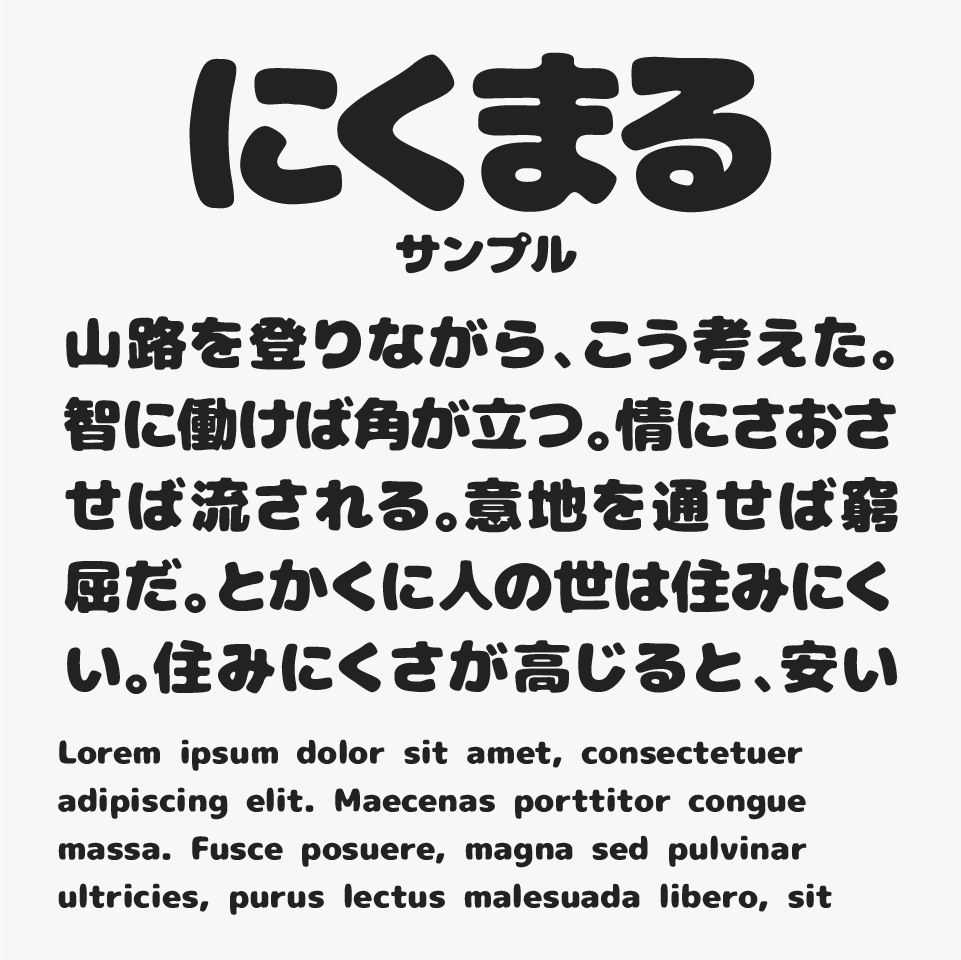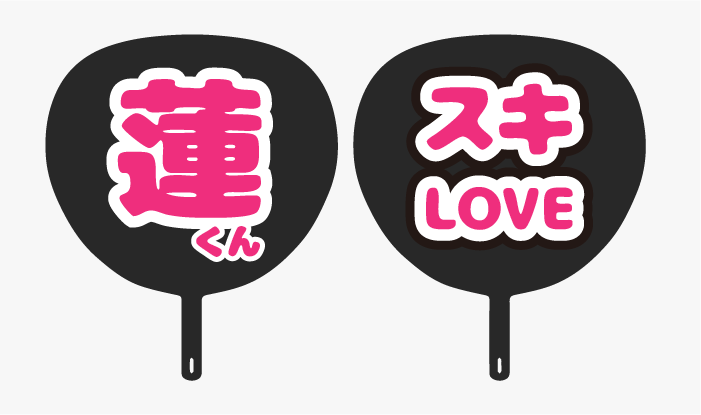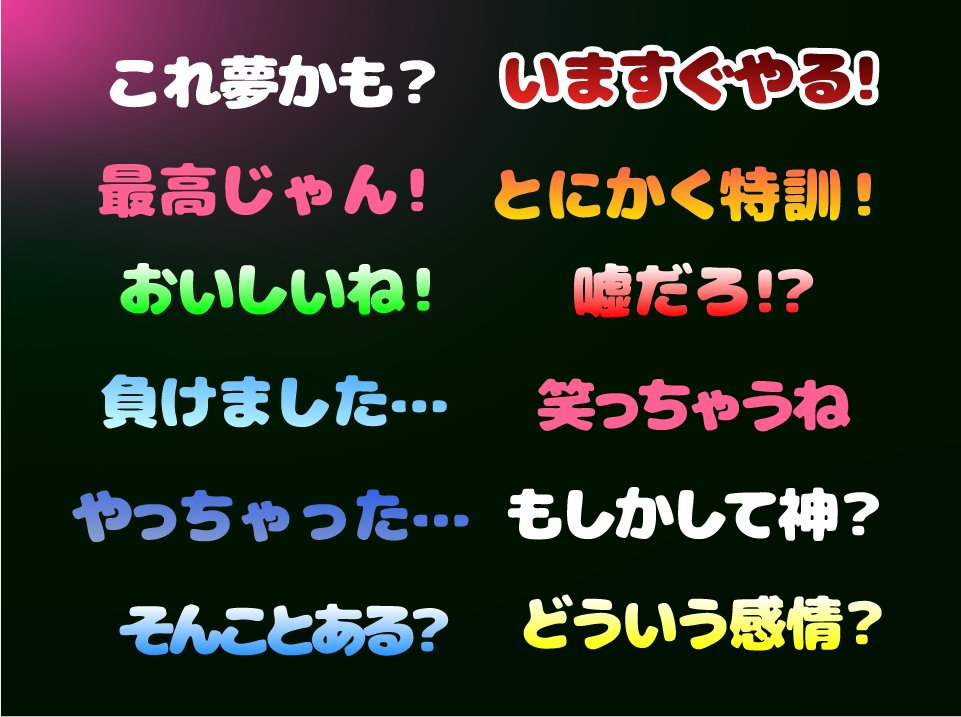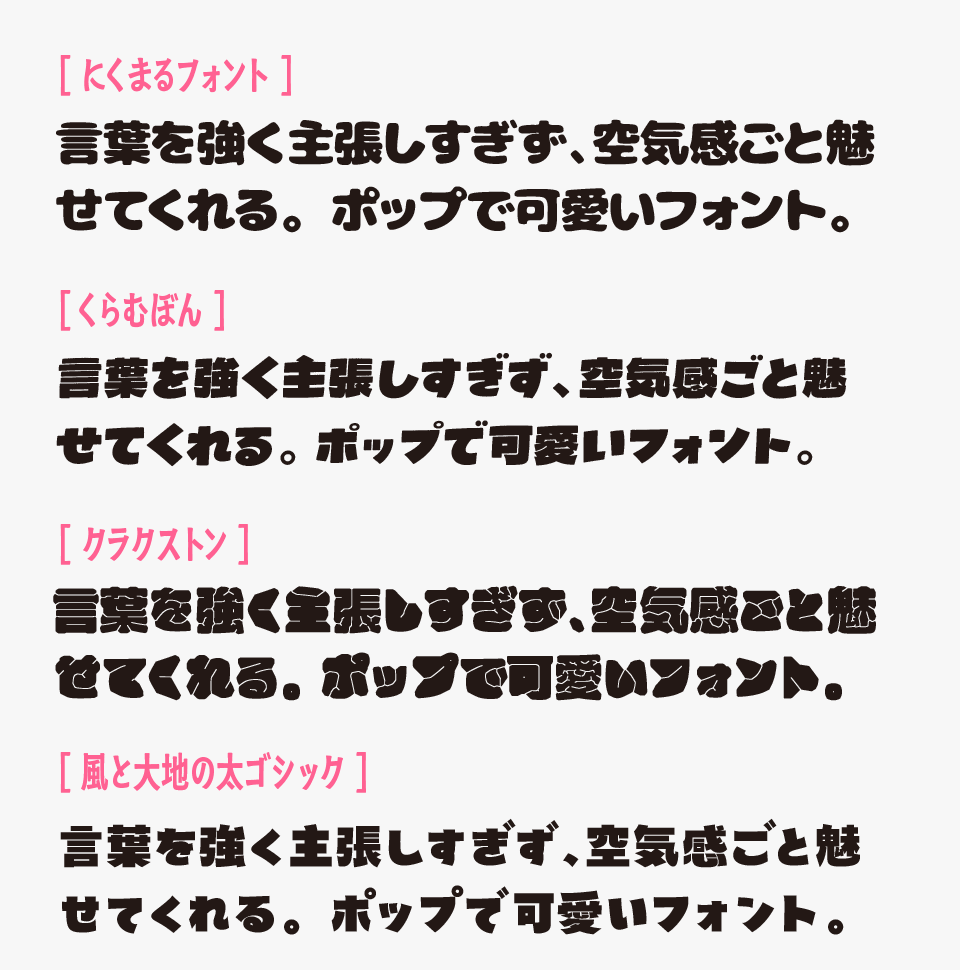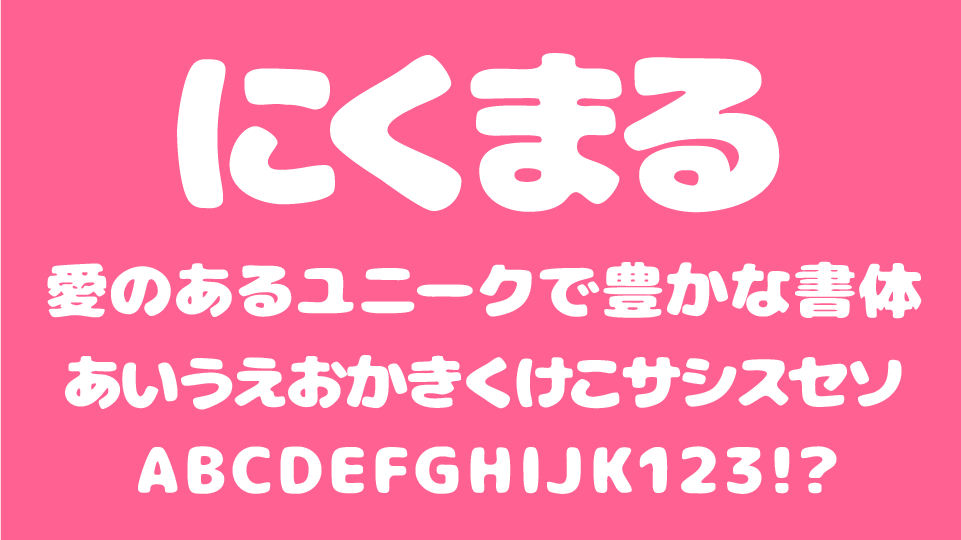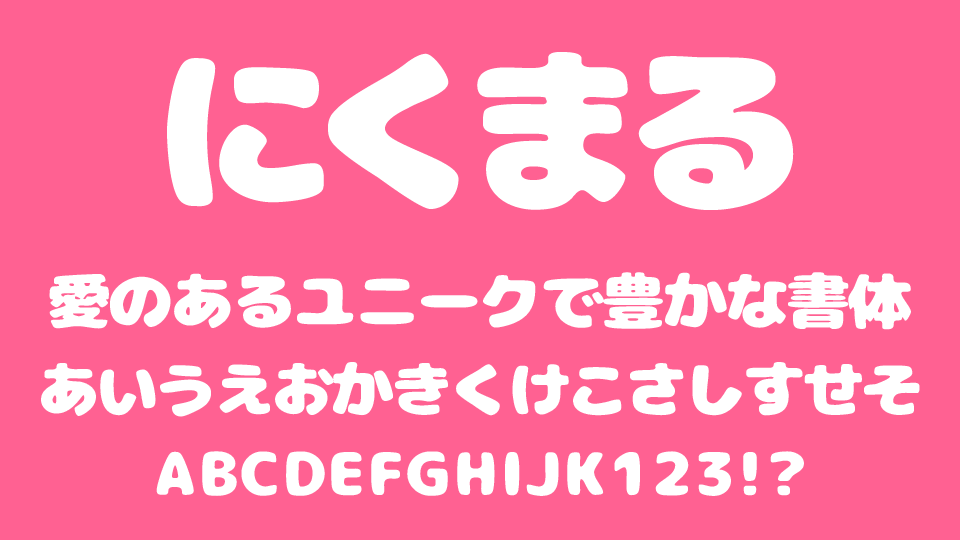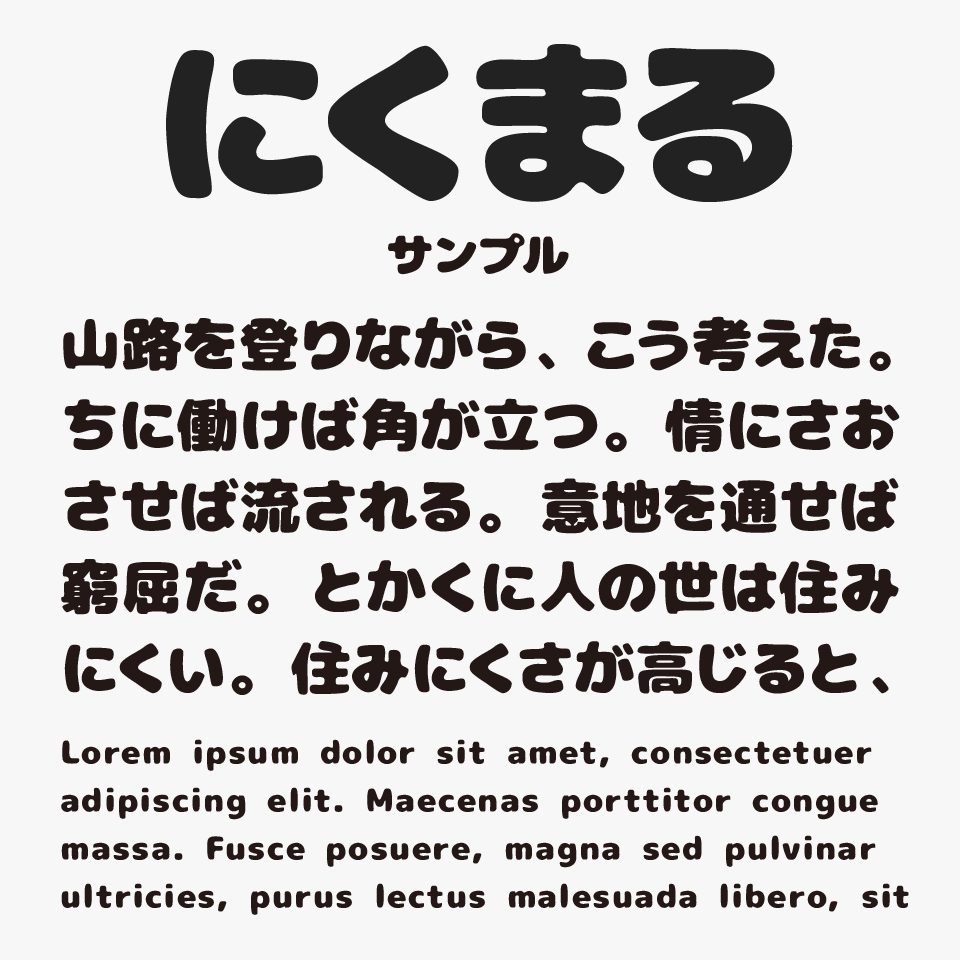
丸ゴシック体・丸文字
にくまるフォントは、M+フォントをベースに丸く太く加工された、ゆるく・やさしく・柔らかい雰囲気が特徴のデザインフォントです。
まるまるっと太ったフォルムが愛らしく、線の太さによるインパクトも兼ね備えているため、ロゴデザインやタイトルロゴ、見出しに向いているフォントです。
アイドルの応援うちわなどの推し活グッズで使用する文字としても人気があるフォントです。応援グッズなど作られている方にもおすすめフォントの1つです。
やわらかく読みやすい文字になっているため、動画制作やテロップ用フォントとしても人気があります。やわらかく読みやすい文字デザインになっているため、画面上でも視認性が高く、会話系動画やVlog、配信テロップなどにも使いやすいフォントです。
にくまるフォントを使った動画テロップ事例
にくまるフォントを、ほかのぷっくりとした可愛らしい雰囲気を持つフォントと比較してみると、ふっくらとした丸みの太さのシルエットが文字の安定感が特に魅力なフォントです。
比較フォントは、「くらむぼん」「クラクストン」「風と大地の太ゴシック」と使用していますが、どれも極太でふっくら可愛いフォントなので、ぜひあわせてチェックしてみてください。
にくまるフォントと、「くらむぼん」「クラクストン」「風と大地の太ゴシック」フォントを比較
収録フォントは、数字、アルファベット、記号、かな文字(ひらがな・かたかな)、教育漢字、常用漢字 第一水準漢字、第二水準漢字(途中まで完成)が収録されているとのことです。